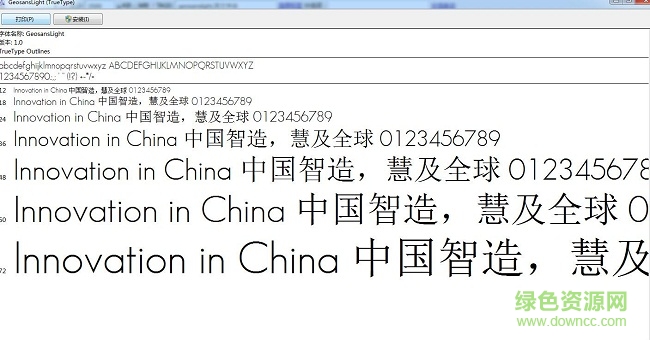
geosanslight字體是一款鋒利的英文字體,該字體有一種獨(dú)特的優(yōu)雅氣質(zhì),用在時(shí)尚雜志、廣告設(shè)計(jì)、平面設(shè)計(jì)方面都可以,需要的朋友快來(lái)下載吧!
無(wú)襯線最廣泛的應(yīng)用是在電子世界。無(wú)襯線和襯線字體相比,就好像鉛筆字vs鋼筆字。鉛筆字的最大特征是非常沒(méi)有特征,極端的平淡。這也是無(wú)襯線字體設(shè)計(jì)的一個(gè)理念:即透明容器理念。說(shuō)的是字體本身不應(yīng)該傳達(dá)任何復(fù)加的意義,而只傳達(dá)文本本身的意義,就好像一個(gè)透明的容器只展示其中的內(nèi)含物而不展示容器的屬性一樣。